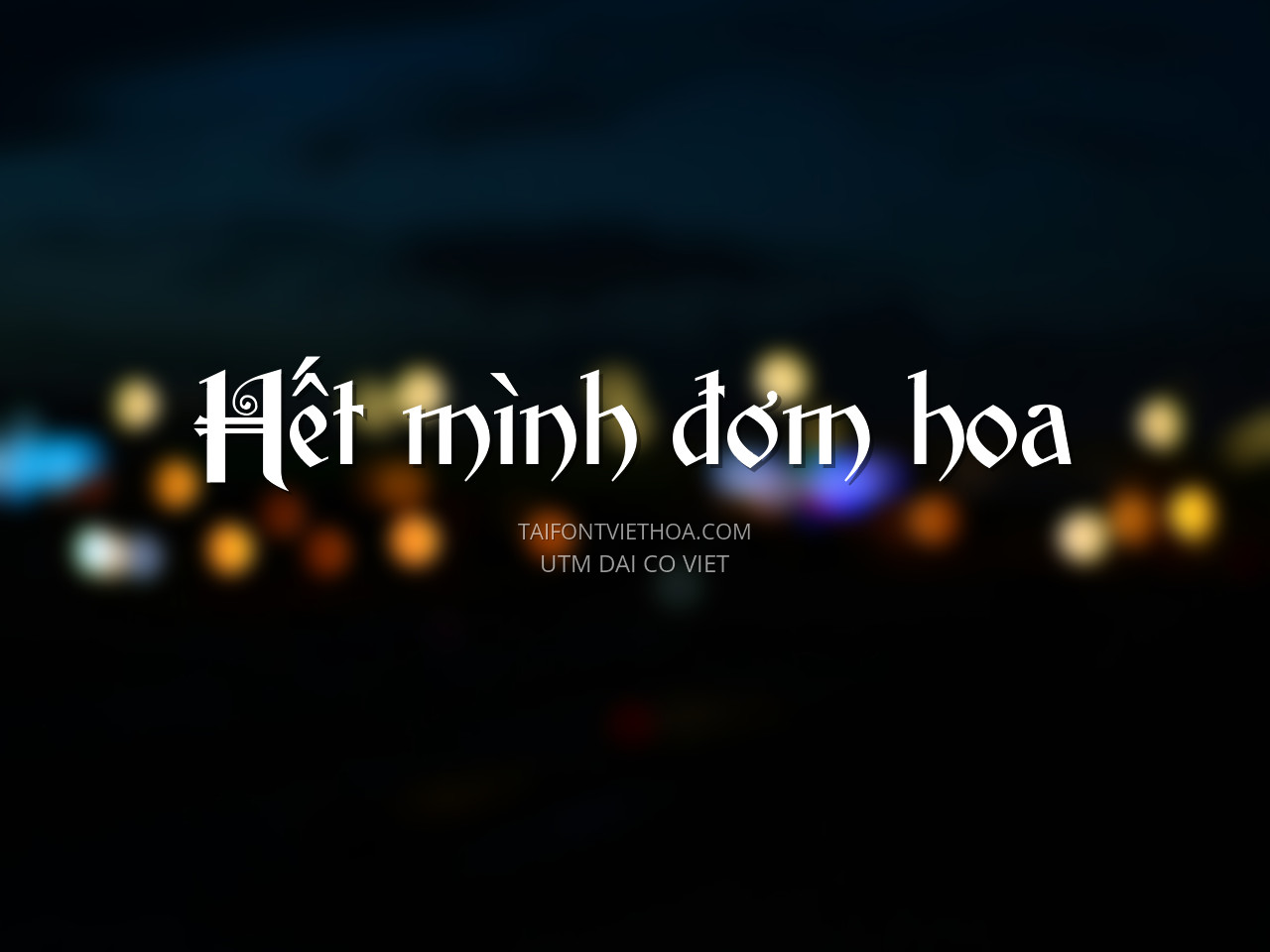
Giới thiệu về font UTM Dai Co Viet
UTM Dai Co Viet là phiên bản Việt hóa của font Dai Co Viet – một kiểu chữ cổ điển mang đậm nét văn hóa và lịch sử Việt Nam. Font gốc lấy cảm hứng từ các chữ khắc trên các di tích lịch sử và văn bản cổ, với thiết kế mang tính nghệ thuật và truyền thống sâu sắc. Phiên bản Việt hóa đã được hoàn thiện để hỗ trợ đầy đủ tiếng Việt cùng nhiều ngôn ngữ khác, giúp bảo tồn và phát huy giá trị văn hóa trong các dự án thiết kế hiện đại.
Đặc điểm thiết kế và ứng dụng của UTM Dai Co Viet
UTM Dai Co Viet sở hữu cấu trúc đặc trưng của các chữ khắc cổ, với các nét chữ vuông vức, dày dặn và cân đối. Font có thiết kế đậm chất nghệ thuật truyền thống, tạo nên sự trang trọng và độc đáo trong từng ký tự. Font thích hợp sử dụng trong thiết kế sách lịch sử, poster văn hóa, ấn phẩm truyền thông di sản và các dự án nghệ thuật truyền thống.
Font phù hợp với các ngành nghề như bảo tồn văn hóa, giáo dục, nghệ thuật, truyền thông và thiết kế nội thất mang phong cách truyền thống. Đây là lựa chọn lý tưởng để thể hiện sự kết nối giữa quá khứ và hiện tại trong các sản phẩm thiết kế.